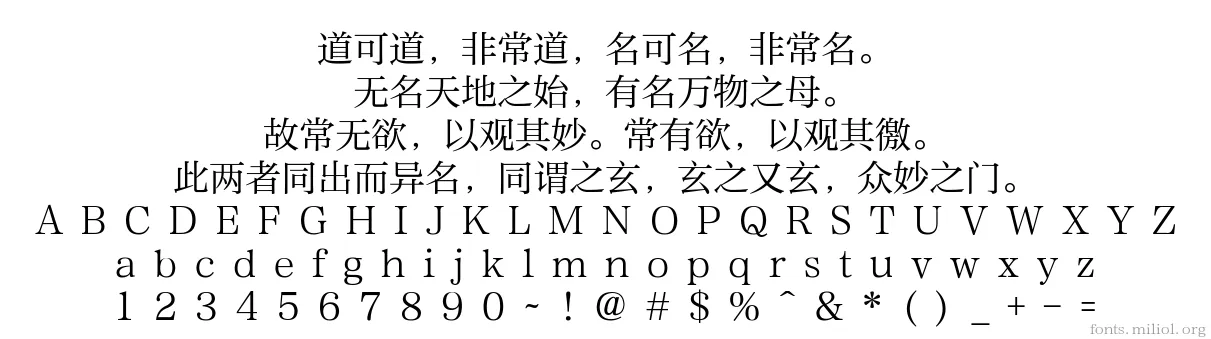
**方正细雅宋_GBK字体简介**
方正细雅宋_GBK(FZYaSong-L-GBK)是一款兼具传统宋体韵味与现代设计美感的字体,隶属于方正字库的经典系列。其笔画纤细优雅,横平竖直间保留了宋体的衬线特征,同时通过适度的弧度处理,赋予文字温润的视觉表现力。GBK编码支持涵盖繁简中文、日韩汉字及特殊符号,适用性广泛,尤其适合书籍排版、杂志标题、品牌宣传等需要兼顾文化底蕴与精致感的场景。
该字体文件命名中的“FZXIYSK--GBK1-0”为其内部版本标识,结构清晰规范,便于专业设计场景调用。作为一款商用授权字体,使用者需遵守版权规定,确保合法使用。方正细雅宋_GBK以独特的艺术性与实用性,成为设计师提升版面质感的优选之一。